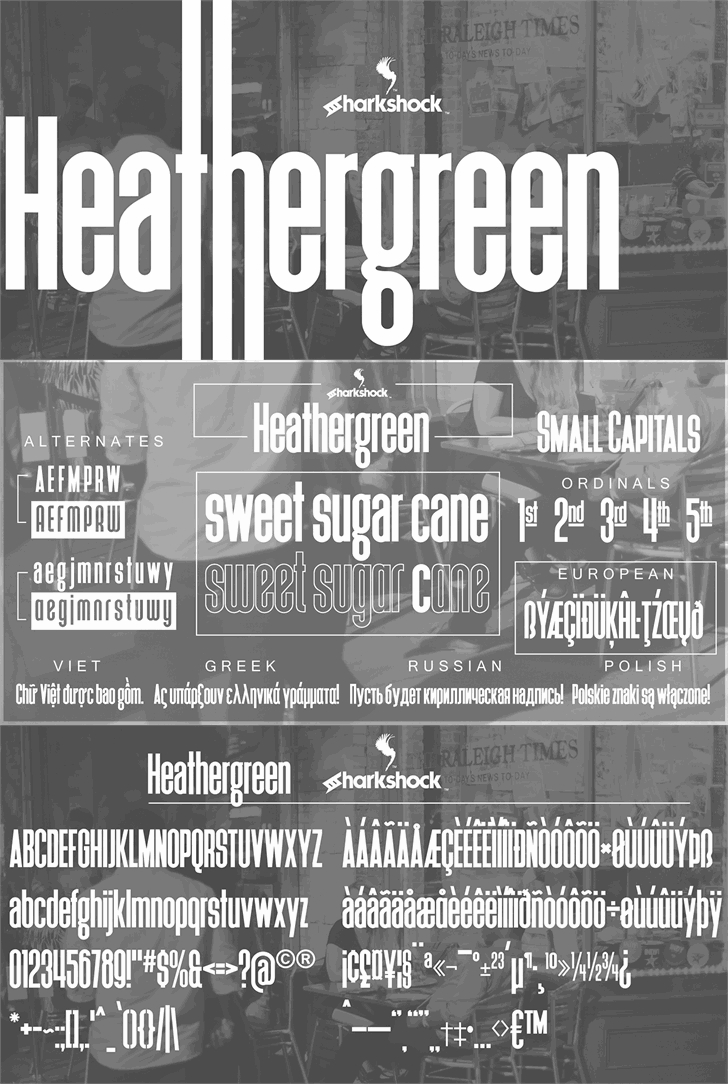
A Heathergreen é uma fonte de display elegante e envolvente, perfeita para capas de revistas ou logotipos memoráveis. Cada caractere parece ter sido desenhado cuidadosamente para transmitir um sentimento sereno e sofisticado ao mesmo tempo. Esta fonte foi criada pelo designer Sharkshock em 2016, com Dennis Ludlow mantendo todos os direitos de autor. Conhecida por seu tom neutro e minimalista, Heathergreen oferece uma paleta vibrante que se adequa perfeitamente a texturas de cor vibrantes ou padrões de design moderno. Ela é ideal para qualquer projeto de design em que desejas transmitir elegância e sofisticação, seja ele um site de estilo único, um aplicativo criativo ou até mesmo uma embalagem de produto minimalista. A Heathergreen não só destaca seu conteúdo, mas também adiciona um toque autêntico ao seu design final, tornando-a a escolha perfeita para designers que buscam uma fonte que combine funcionalidade com beleza.
Designer: Sharkshock